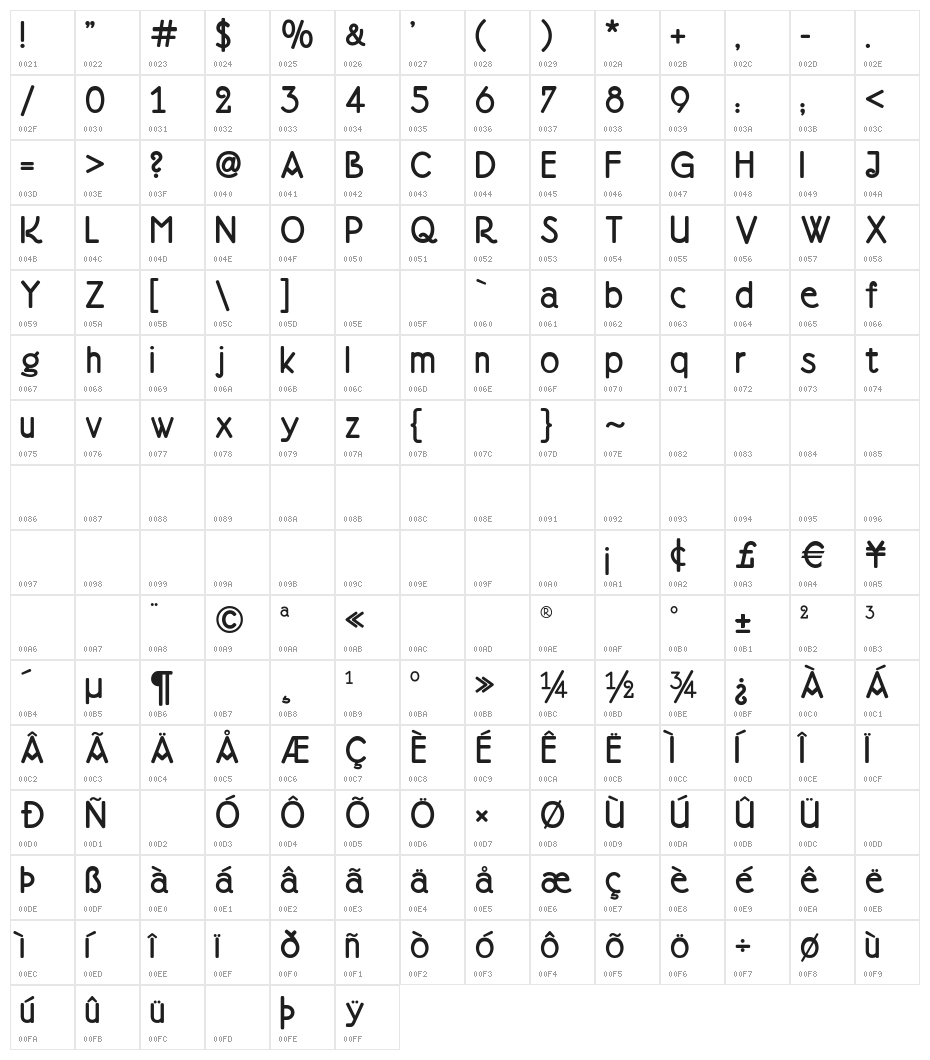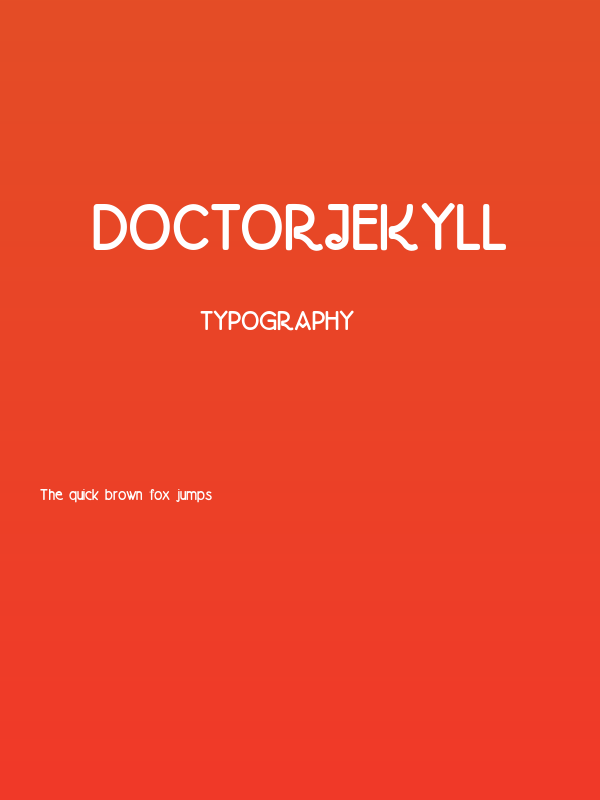
DoctorJekyll Font
| Anwendungsfall | Headlines, Logos, Digital content |
| Vorgeschlagene Projekte | Ideal for children's books, playful branding, casual invitations, and digital content aimed at a youthful audience. |